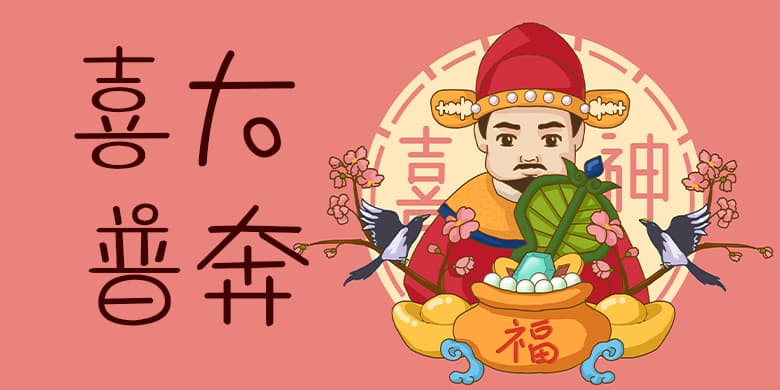
品牌:方正手迹设计师:孙健营发行时间:2020字库编码:大陆简体(GB2312-80)分类:创意书写字体属性:精品字
喜大普奔体,这款大量的使用圆形元素,口、日等封闭空间都处理为圆形,一些点画也巧妙处理为小圆圈,大量部件与圆圈搭配使用,显得欢喜普奔,喜气洋洋。适用于儿童类的书刊、品牌广告和产品包装设计,以及社交网络的个性化用字。